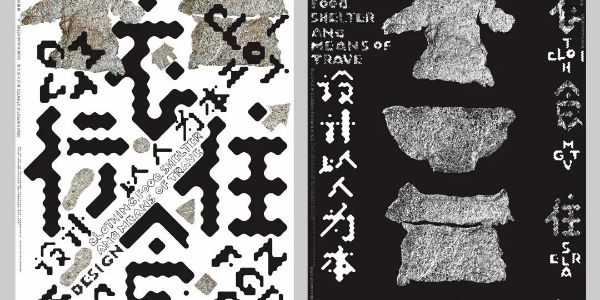
徐伟:汉字造境,一字一韵
本期嘉宾:徐伟(站酷ID:zenith徐伟)亚洲中韩设计协会成员;南京平面设计师联盟会员;汉字境/一字禅全国发起人;字魔营公益社区创始人;浙江中天文化股份创始人、CEO;淬品牌研究事务所董事;缮.社视觉探索联合发起人。
近期重要展赛经历:
玻利维亚BICeB国际海报双年展
斯洛伐克巴尔约代夫国际海报四年展
GRANSHAN德国非拉丁文字体设计大赛特别奖
德国ANFACHEN火花国际海报设计奖
第四届亚洲.上海国际平面设计双年展
斯洛伐克国际海报三年展
第12届日本富山(TOYAMA)国际海报三年展
2018波兰霍如夫海报节
第四届莱比锡国际海报展
2018第三届字酷文字艺术设计展
2018第三届深圳国际海报节
2018北京国际设计周《第二届当代国际水墨设计展》优秀奖
2018波兰克拉科夫入选联合国教科文组织世界遗产名录40周年纪念海报大赛
2018第一届中国印刷艺术设计双年展银奖
2018第二届匈牙利布达佩斯国际海报节
2018秘鲁国际设计双年展
2018亚太设计年鉴
2019波兰反暴力国际海报大赛
2019卢布林(Lublin)国际海报双年展
2019第二届深圳环球设计大赛
2019中国设计年鉴
2019澳门设计大奖
2019巴尔代约夫设计邀请展
2019澳门回归20周年海报展
2019土耳其第三届国际“器官移植”海报设计大赛
2019台湾国际平面设计奖
2019祖国您好庆祝新中国成立70周年海报大赛(上海)
策展项目:
2018苏州“年文化”海报设计邀请展
2018畲文化海报设计邀请展
2019浙江城市美术双年展
2019抚顺雷锋精神国际海报邀请展
2019立陶宛“汉字现象”国际海报设计邀请展
2019“纹藏中国”设计展荷兰站
2019海峡两岸“源有汉字”海报邀请展
2020鼠生肖中国高校设计大赛
2019济南首届家文化海报特邀展
2019印象济宁创意设计邀请展
2019北京国际设计周水墨与纹藏国际设计展(联合策展人)
我们每天都和汉字打交道,它是记录我们语言的符号。曾经我们的祖先在生活中用“图画”来表达自己,慢慢的衍变成了一种“表意符号”。如今汉字作为唯一仍在使用的表意文字,是世界文字中独一无二的存在。
汉字独特的魅力,可以引发我们美妙而大胆的联想。因为中国自古就有“书画同源”一说,书与画好比是兄弟,同根生,有很多内在的联系。
本期嘉宾徐伟(站酷ID:zenith徐伟)老师生长于江南古城,自幼受传统文化的熏陶,习字练画。对于传统的艺术形式,他有着更深刻的情感。他对中国传统艺术的偏爱,也从设计作品中传递出来。
他的“一字禅”作品,以字寄情,一字一韵。在一撇一捺之间,赋予汉字更多的解读。
K:请您先介绍一下您的成长经历。
徐:我出生在江南水乡的一座古城——浙江海宁,这是一个人文底蕴深厚、名人乡贤辈出的地方。大家肯定听说过徐志摩、王国维、金庸、蒋百里等,这些巨匠都是土生土长的海宁前辈。我从小受到家庭熏陶,习画练字,很早跟着长辈们学习了中国传统文化。这些印记在成长过程中给了我很大的帮助,因此我的设计工作也离不开传统文化的影响。
我上大学之前,在一家我们本地的国企工作,最初的职业是个电气技工。由于领导知道我喜欢写写画画,就安排我在企业工会里做宣传工作,就是现在大家所说的“美工”。后来自己不安于现状,参加了高考,顺利考上了宁波大学文化与传播系(艺术学院的前身)。
2002年初,我正式脱离浙江报业集团,开始独立自主创业。其实我们每个人的成长经历不同,期间会有各种原因的挑战和机遇,所以每个人走的路会不一样。
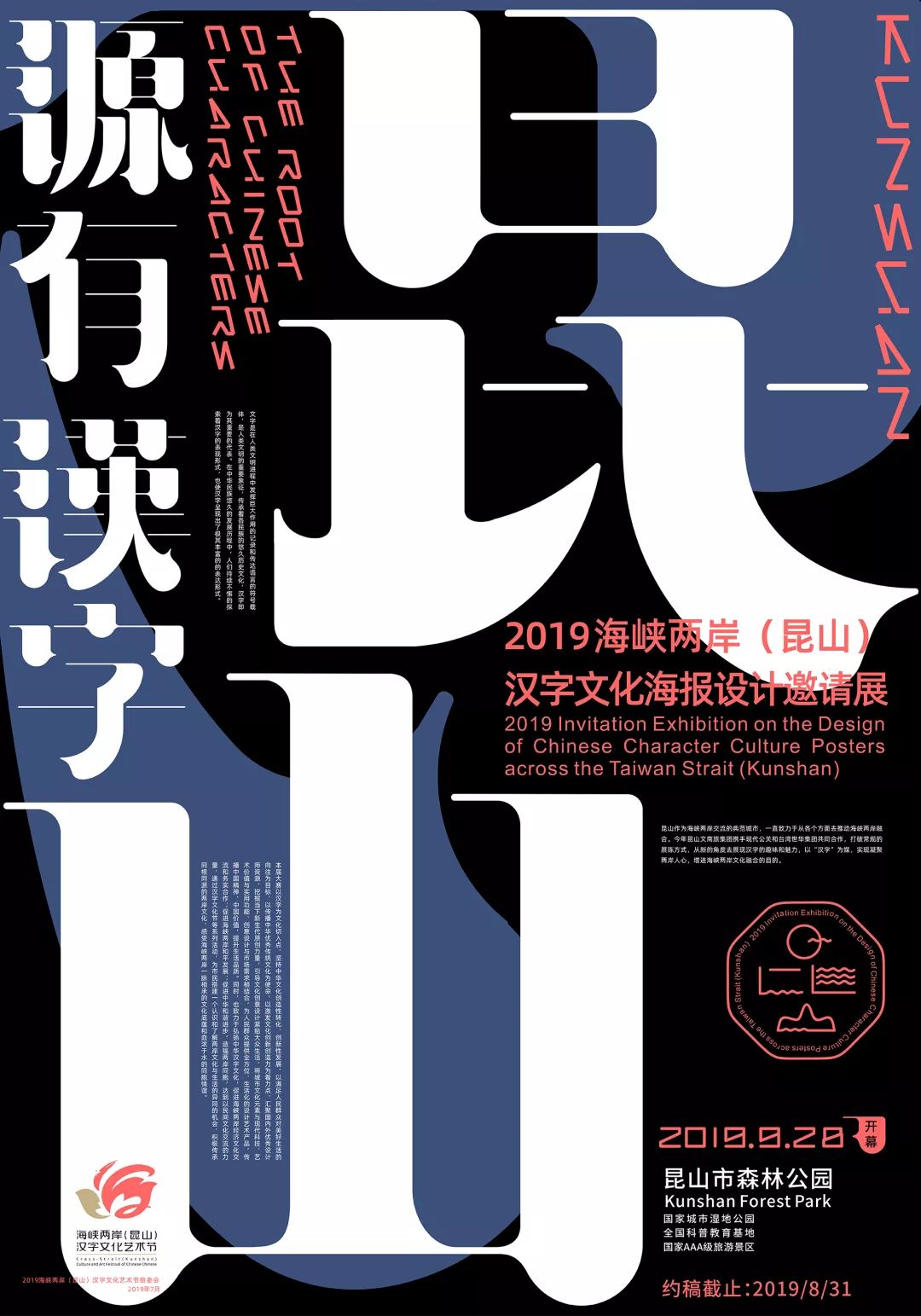
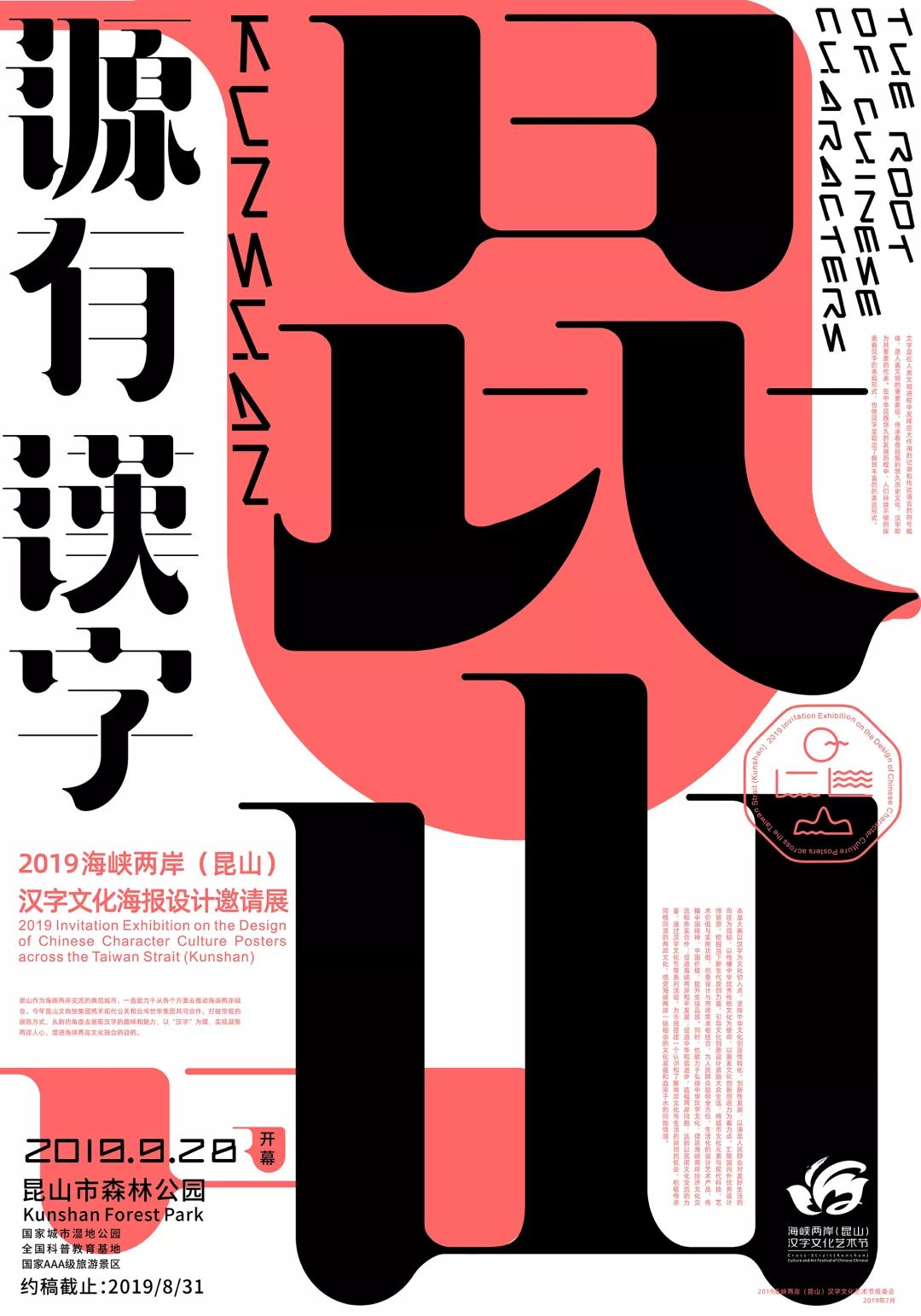
- 2019海峡两岸汉字文化海报设计邀请展 -
K:在您的设计生涯中,有没有人对您有过影响?
徐:1990年,我在工会做宣传。那个年代,是没有电脑这玩意儿,全凭手上功夫,跟着单位老师傅们天天写大字、印宣传横幅、画墙报墙画、活动舞台设计、背景墙徒手刻美术字……虽然很辛苦,但是学到了很多基础性的实践技巧。
读大学期间,我很幸运的遇到了一位在我人生中很重要的老师,是他引导我真正进入视觉设计领域。就是当时教我们视觉设计的蒋华老师,现在任教于中央美院设计学院,AGI会员。
他是一位真正的具有学术高度和感性认知的视觉设计教育家。回想他在教课之余,一直在研究国际学术海报设计和汉字设计探索。当时他就跟我们学生提出“内化于心,外化于行”的理念。这句话应用在设计上,是指从内部做到心中有数,胸有成足;在外部做到表现手法与视觉呈现一致。想法和执行不混乱,可以坦然面对问题,不会杂乱无章,呈现的作品自然美妙。
学生时代的我感悟不到这句话的真正含义,一直到我进入工作状态,在实践中才切身体会到这核心理念对自己的学习、思维、工作是能够影响一生的。所以我想说的是,优秀的老师不教技法而是传授心法。他可以给你方向和方法,因人制宜的引导你开拓创作思维。
K:可以跟大家分享一下,您的创业经历吗?
徐:我创业之初,互联网远没有现在发达,商业参考资源很少,与外界的沟通交流几乎是没有的。业务沟通、设计、后道等流程都是我一个人完成,虽然很苦,但是很磨练人。
很多知识在学校是学不到的,只有通过实践慢慢领悟。比如对宣传册纸张不了解、纸张怎么开不耗材?工艺应用出来效果怎么样?平面之外的空间设计灯光怎么用?与客户的谈判怎么说恰到好处?一大串的问题等着自己摸索。这样的方式开启自己的创业之路也许对于年轻创业者来说是一个很好的积累和借鉴。
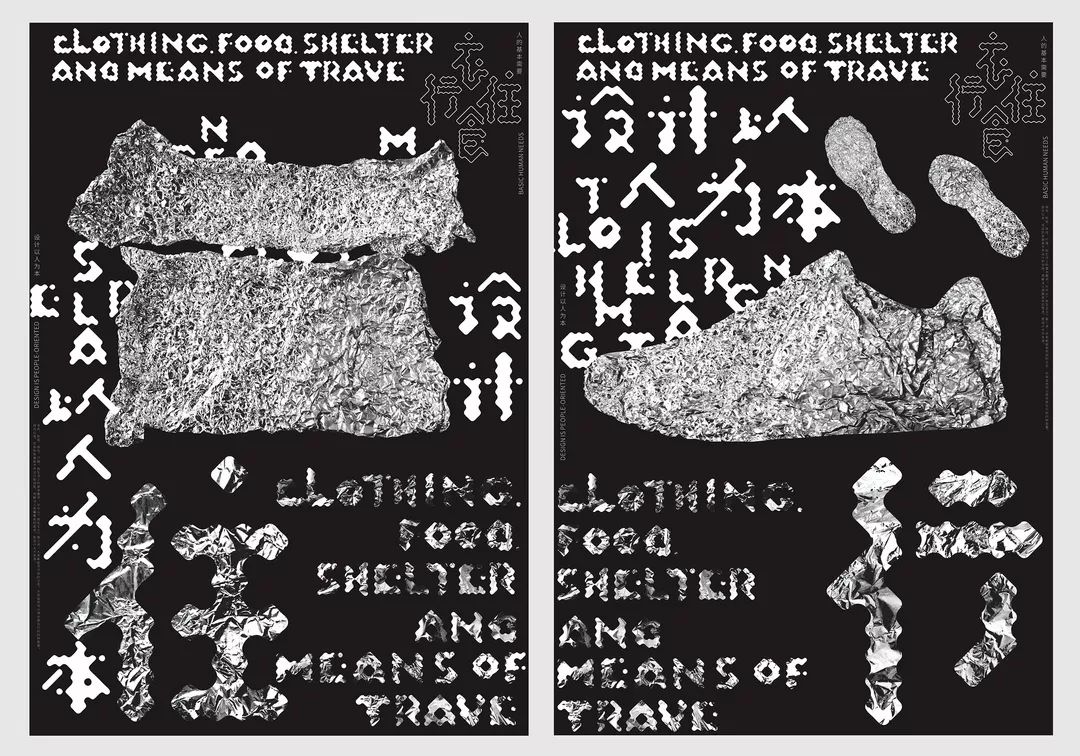
- 衣食住行 -
K:一字禅汉字造境的概念从何而来?
徐:很多人问我:“一字禅”究竟是什么概念?我借用六能祖师的佛性观来表述:“妄念本寂,尘境本空。寂寂之心,灵知不昧,即是空寂之知,是汝真性。任迷任悟,心本自知,不藉缘生,不因境起。知之一字,众妙之门。”
通俗来说,就是借助禅学理念,应用在自己的日常生活与工作当中。我把它看成是“通过一个字韵字意表达当下自我的心境”。就像有人喜欢写日记、有人喜欢种花草,有人喜欢喝茶,一样的道理,都是一种对生活积极的态度。
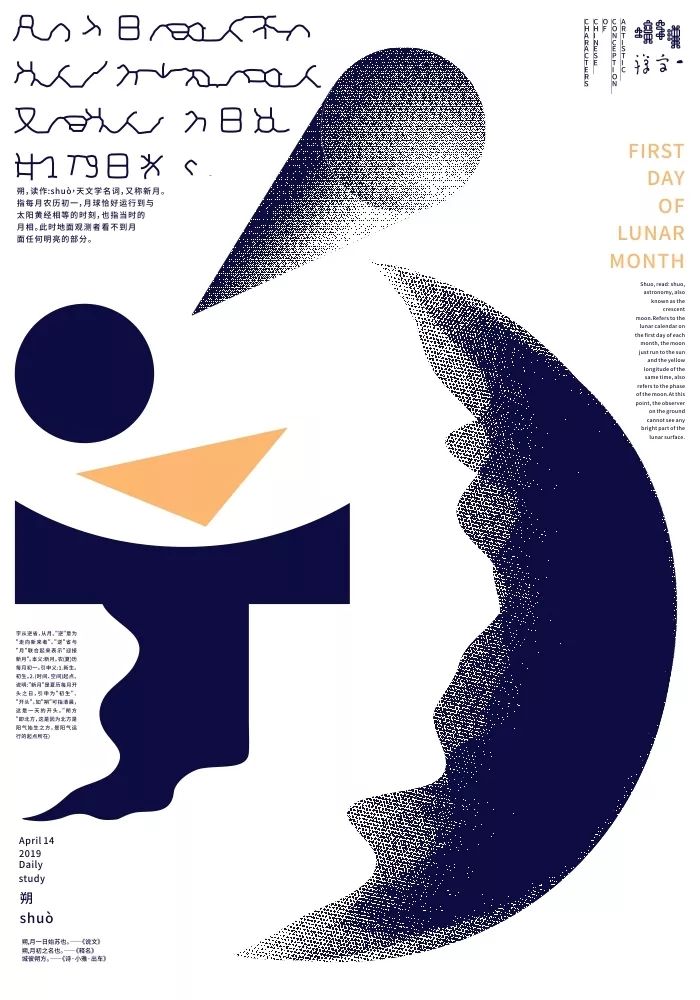
- 一字禅汉字境 - 朔 -
大方广师《子吼经》说到:“一字者,一理之名字也。理本无名无字,超心意识,离性离相,无作无示,非诸众生所能思议,惟佛如来究尽明了。经云:法惟一字,所谓无字。是也”。其实这段话已经讲到了心境与创作的平衡,也就是前面我说的讲到的“知行合一”,一个字体可以代表万物,也可以代表自己本真,完全取决于自己的,一切遵循自己内心的。
至于“汉字境”定位来源,要想知道汉字的起源,就得真正的了解中华上古历史。几千年以来,人们遵循着眼见为实的理念,去寻觅历史留下的痕迹。现在很多人用“xx造字”,我觉得不妥,是对先贤的不敬。汉字能够纵横中国几千年不衰,正是因为文脉代代相传,我们后人怎么能用“造字”这个概念,这个敬畏心必须要的,所以我就用了“汉字境”这个词。
K:您是怎样保持自己的创作灵感的?
徐:我在繁忙的工作之余,保持每天抽出一个小时进行字体设计训练,哪怕自己出差在外也时刻安排好时间做一些练习。这不是一种为设计而设计的方式,而是通过这种方式加强自己对事物的认知;训练自己在短时间内做出反应,这就是所谓的“初心”,第一时间怎么想的就怎么做。
我没有刻意让自己知道明天需要做哪个字,而是到了明天再查看轮到哪一个字……这样的方式,我最大的感触是让自己保持时刻敏锐的思考能力,可以在自己的商业活动中、设计执行中为自己带来很大的帮助。我之前和朋友所说的“时间成本”对于设计师来说真的是生命线。
K:您觉得类似“一字禅”这种练习对工作的帮助有哪些,还有哪些刻意练习的方式可挖掘。
徐:我做一字禅汉字造境的研习已经坚持了3年多了,最初的想法是通过练习,让自己保持这种思维的活跃性。
要知道肌肉和骨骼需要锻炼,你的脑细胞更需要让它们得到锻炼,通过这种形式的训练,嫁接到自己商业设计中去,你会发现原来任何设计就是这样玩出来的,探索与实践都是相通的,天才之说都是假的。
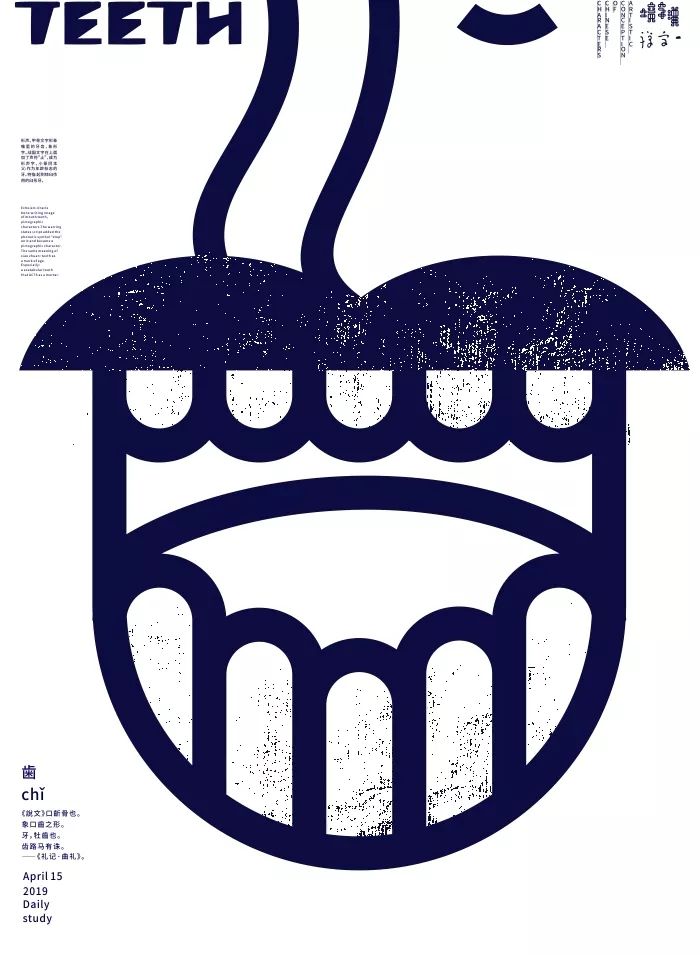
- 一字禅汉字境 - 歯 -
我前面所讲到的,一字禅的自我练习方式,能够让自己保持这种敏锐的思考能力,可以在自己的商业活动中、设计执行中为自己带来很大的帮助。比如说,甲方一个突击项目,在常规时间不允许的情况下,我可以在极短时间内精准部署,不会模棱两可“试试看”这种做法,迅速判断分析该项目可不可行,这样做对双方都有益。至于哪些地方还可以挖掘?
我到时觉得通过一字禅学习,更大层度的了解一些非常用字的来历和出处,因为我们每个汉字都是一部历史教科书,一种注满智慧的哲学,一次以古人交流对话的机会。生在当代穿越千年,用今人的方式去解读古人的生活、人文、故事,真的是比追剧有趣得多。
K:您是如何通过海报表现个人的情感的?
徐:近年来随着公司的业务和管理层趋于稳定,我重新回到了自己最喜欢的非商业海报设计当中,参与了一些国内外大赛和专业展览,目的是拿自己的练习作品与外界交流,通过这样的交流可以看到自己的不足。
我做海报不是为了展览、比赛而可以去准备的,我一直觉得是靠平时的点滴积累,每天抽取一定时间,把所见所闻利用图形和字体结合的方式用草稿形式记录下来,这是海报创作的重要信息资源和可靠元素,慢慢的积累起来,时事类的、政治类的、社会问题、生活趣事、环境问题、人文地理等等感兴趣的东西进行记录,为未来的展赛交流做基础的信息储备。只有这样,让自己始终保持一种对事物的思考活跃度。
在正式进入创作阶段,我会根据主题进行分类思考,寻找与主题相关的关键词,查阅相关资料等,然后草图进行推演测试,因为艺术海报设计形式的创作手段千千万万种,找到适合自己、最符合主题语境的、最本真自然流露的、自己血液里流淌的东西去执行表达。
- Let him to shut up -
K:您的情感表现用到最多的视觉元素是什么?
徐:对于创作,有时候我会拉上女儿帮忙,我从孩子身上看到了大人无法做到的天趣,通过与女儿合作的方式参与了不少比赛,也得到了国际社会的认可。发现一个有趣的现象,夸张并且出人意料的造型,往往会获得更多人的关注和喜爱,这也许就是设计源自真情流露吧。
很多时候,在自然状态下,我创作一件作品,会不经意的用自己最喜欢的中国语境表达,字体也好、图形罢,讲水墨、宣纸、筷子、印章、器物等等一切中国元素融入其中。可能我自己骨子被这些中国符号给烙印了,抹不去了。
- 求同存异 -
K:很多设计的初学者看到艺术海报认为没有意义,他们认为这些不是商业设计,对自己的工作没有太大帮助,所以很多时候都选择拒绝学习,对此您怎么看?
徐:我喜欢与年轻的设计师以及准设计师们进行交流,发现这些年轻人都很好学,特别有想法,思维活跃,比我们这一代人年轻时候优秀多了。但是在他们身上也看到了一些时代通病,快节奏的工作、无休止的熬夜、价值观取向等等。他们当中很大一部分人对我们自己民族的东西不屑一顾,认为很老土,其实他们不知道老外们偏偏对中国的汉字、文学、书法、水墨都别感兴趣,老外都喜欢的我们有什么理由扔掉它呢?
- 《衣食住行》系列 -
设计思路:我喜欢用生活中常见的东西来进行创作,这套作品创作于2018年初,是用锡箔捏出自己需要的形态,进行拍摄和简单后期处理,进行版式和空间关系的调整,最后出来是这样的效果。
穿衣、吃饭、居住、行路。是生活的基本需求。自古以来,社会的发展离不开设计和创新,解决人类最基本的需求,就是设计的本源。这套作品入选温州国际海报双年展、深圳环球设计大奖、2019台湾国际平面设计奖等。
- 茶语心境 -
- GOD'S GIFT -
- hurt each other -
- Man's jass -
- power destroys peace -
- 荷色生香 -
- 孔孟之道 -
- 西湖十景 -
- 金冬心楷 -
- 菱珑昆山-菱 -
- 汉字境-囦 -
- 汉字境-赏 -
- 汉字境-峋 -
- 汉字境-悾 -
- 汉字境-仨 -